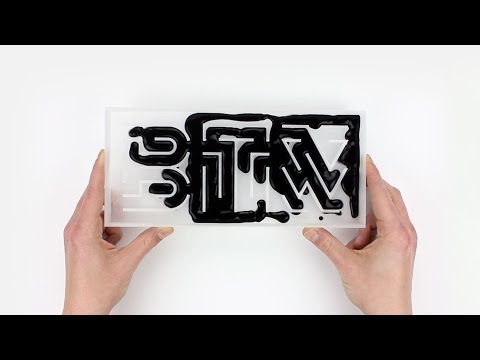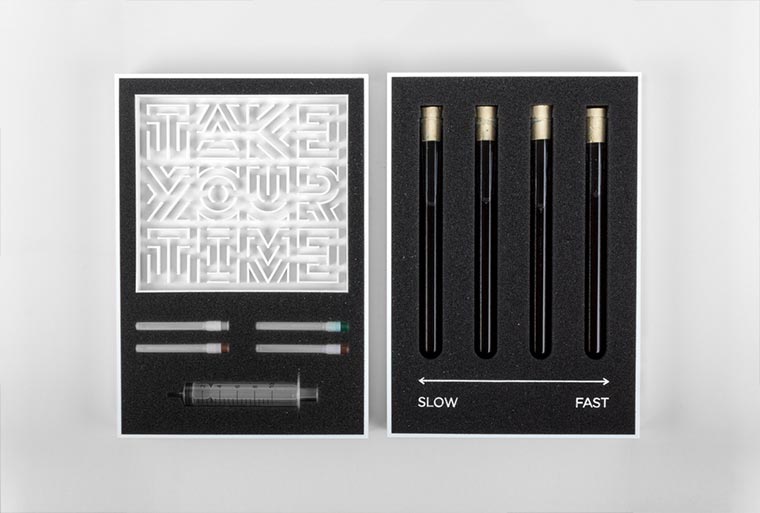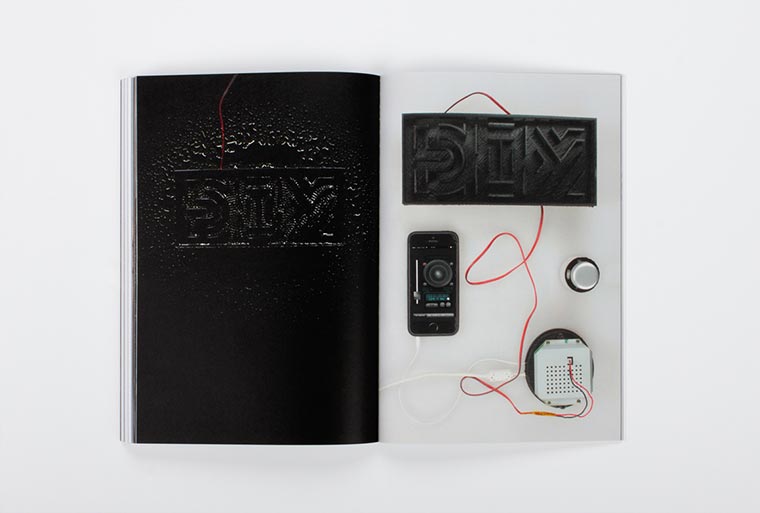
Typografie und Materialität
3D Font aus physischen Prozessen
Ein sehr interessantes und gut gemachtes Abschlussarbeitsprojekt des Kommunikationsdesigners Thomas Wirtz, der Typografie mit Physik mischt. Ein selbst entworfener Font wurde bei By the Way – Typografie und Materialität 3D-gedruckt und unterschiedlichen Prozessen ausgesetzt. Ob durchfließende Flüssigkeiten, brennendes Feuer oder andere experimentelle Dinge – alles führt dazu, dass die Schrift entsprechend sichtbar wird.
„By the use of various media, the master thesis describes a free design experiment that has evolved over time into a modular system consisting of two components: The self-made font, produced by 3D printing, which is thereby associated with a variety of physical processes.“
BTW – Typografie und Materialität